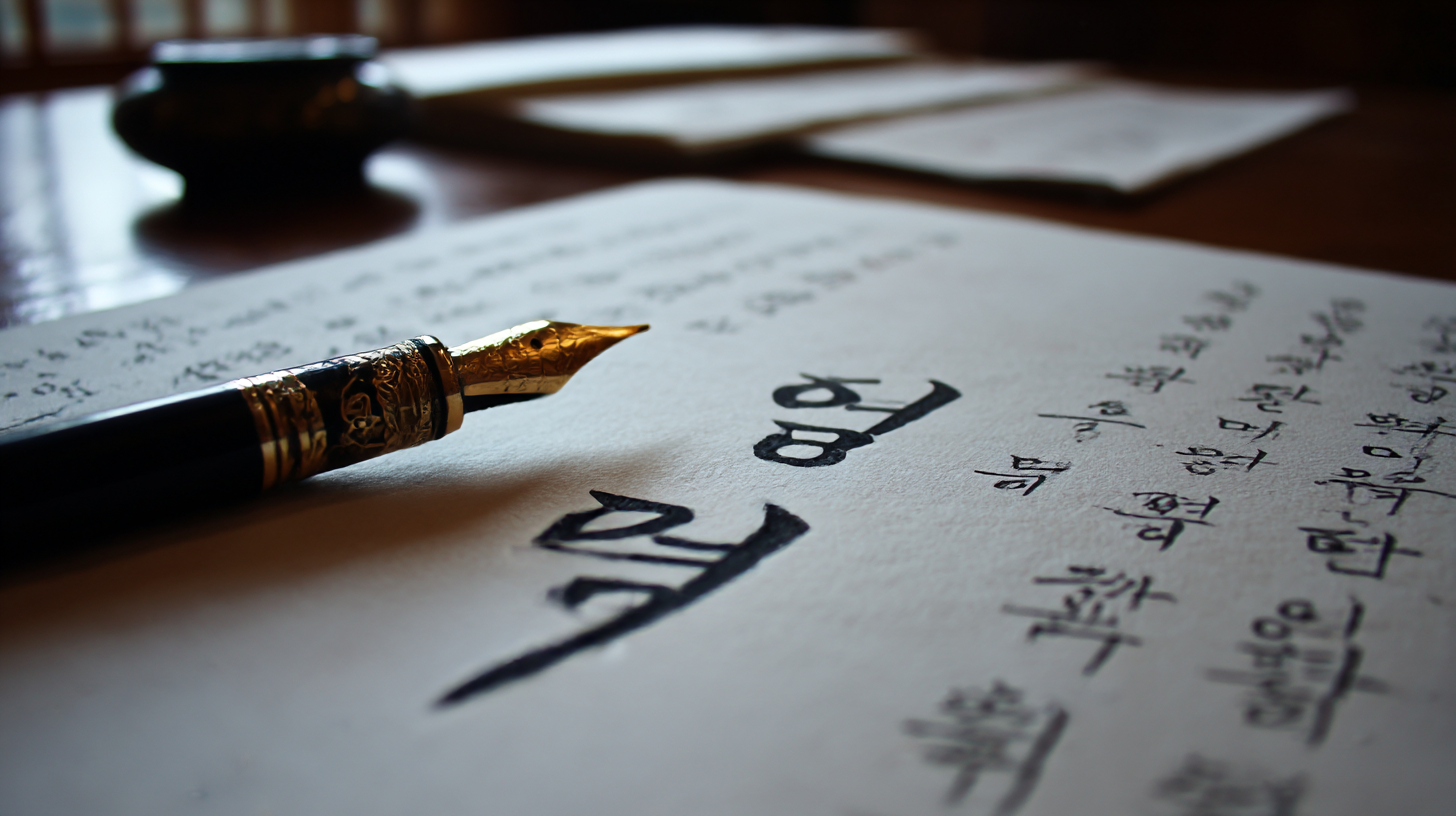
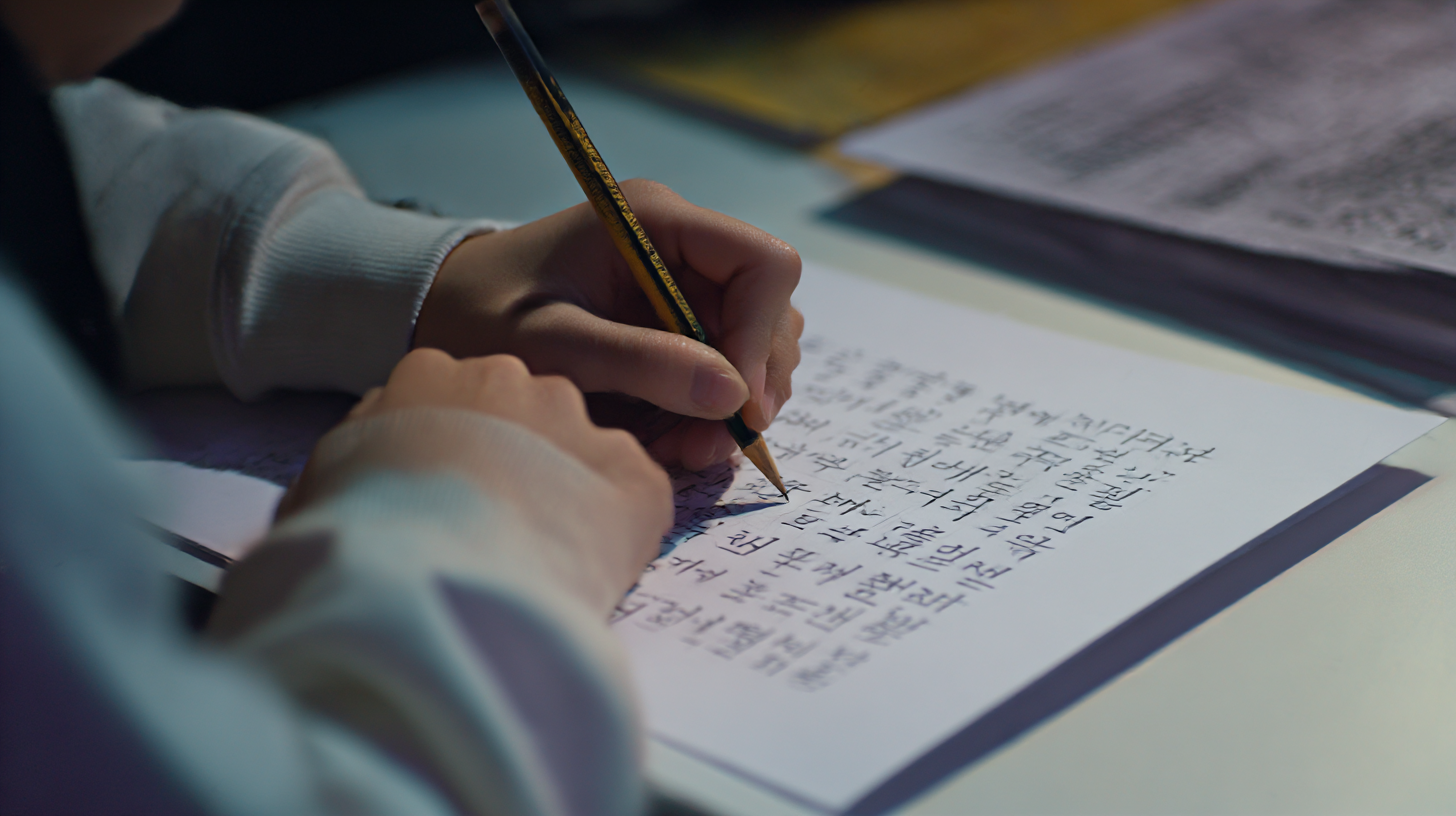
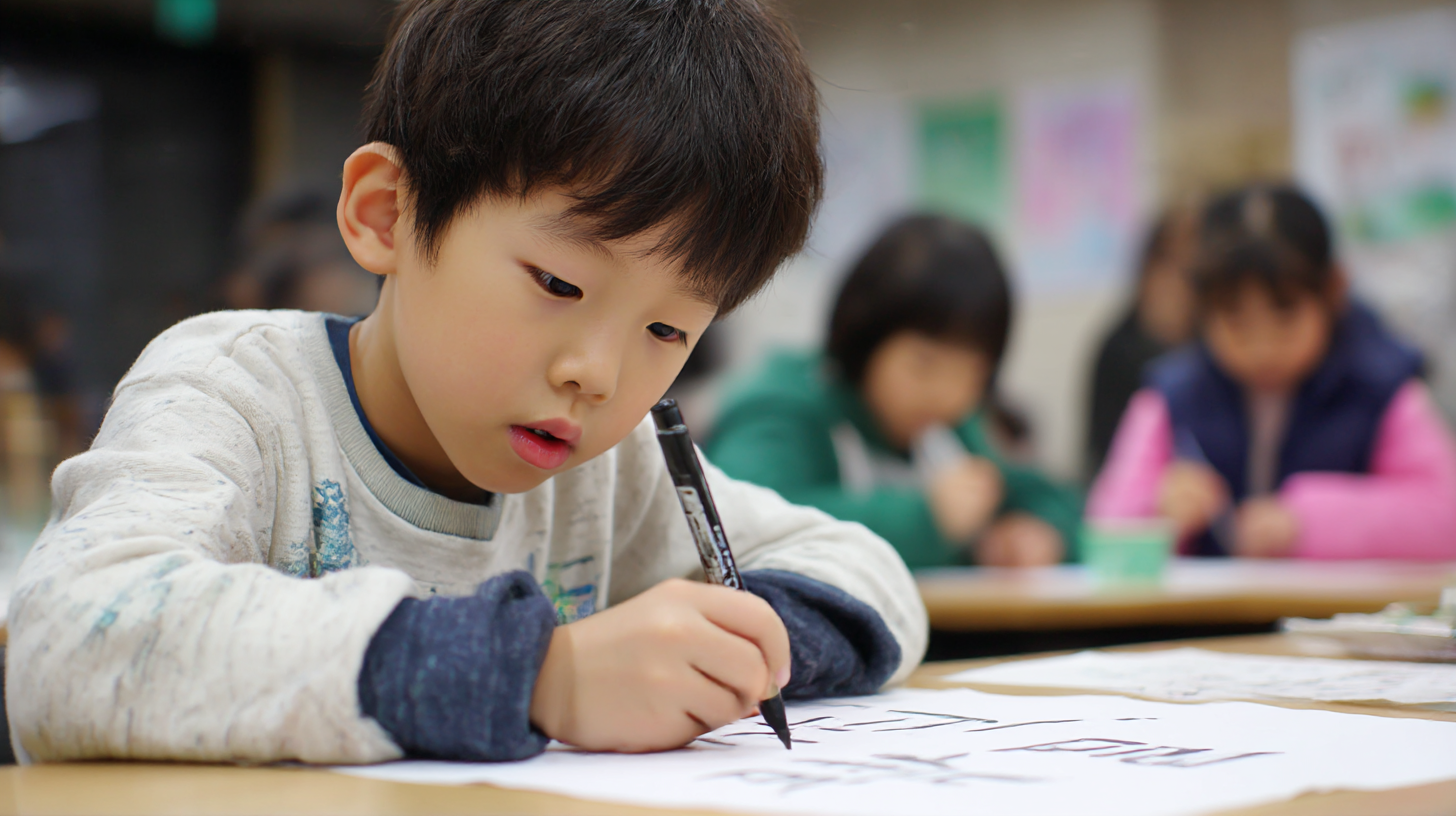
바른글씨 따라쓰기 효과적인 연습법 글씨는 그 사람의 첫인상을 결정짓는 요소 중 하나예요. 디지털 시대에도 손글씨의 가치는 여전히 유효하죠. 특히 학생이나 직장인들 사이에서는 바른 글씨체를 통해 가독성을 높이고, 집중력까지 향상시키는 효과를 기대할 수 있답니다.
이번 글에서는 따라쓰기 연습을 통해 어떻게 바른글씨를 만들 수 있는지, 실질적으로 도움이 되는 루틴과 도구, 그리고 많은 사람들이 겪는 궁금증까지 하나하나 풀어보려 해요. 직접 경험한 듯한 생생한 꿀팁도 가득 담았으니 끝까지 읽어보세요!
✍ 바른글씨의 중요성
글씨는 단순한 기록 수단이 아니라, 자신의 생각을 시각적으로 표현하는 방식이에요. 사람마다 글씨체가 다르기 때문에, 글씨만 봐도 그 사람의 성격이나 정서를 느낄 수 있어요. 예를 들어, 정갈하고 반듯한 글씨를 보면 그 사람의 성실함이 느껴지고, 흐트러진 글씨에서는 급한 성격이나 산만함이 느껴지기도 하죠.
바른글씨는 첫인상에서 중요한 역할을 해요. 이력서를 쓸 때나 메모를 남길 때, 손으로 쓴 글이 상대방에게 주는 인상은 꽤 크답니다. 글씨가 깔끔하면 내용까지 더 신뢰감 있게 느껴지는 법이죠. 특히 교사, 강사, 디자이너처럼 손글씨를 많이 활용하는 직업군에서는 글씨체가 곧 전문성을 나타내기도 해요.
또한, 바른 글씨를 쓰는 습관은 학습 능력 향상에도 영향을 줘요. 또박또박 정리하며 쓰는 과정에서 내용을 더 깊게 이해하게 되고, 반복적으로 쓰면서 암기력도 자연스럽게 올라가요. 실제로 글씨 교정을 시작한 많은 학생들이 공부에 더 집중하게 됐다고 말하곤 해요.
내가 생각했을 때 글씨는 자기관리의 시작이에요. 바른 글씨를 쓰기 위한 꾸준한 노력은 결국 자신의 삶을 정리하고 다듬는 과정과도 같거든요. 단순히 ‘예쁘게 쓰는 것’이 목적이 아니라, 자신을 표현하고 소통하는 더 나은 방식을 찾는 것이라 할 수 있어요.
바른글씨는 마음가짐까지 달라지게 해요. 글씨를 정갈하게 쓰려고 하면 몸도 자연스레 자세를 고치게 되고, 집중도도 올라가죠. 이런 작은 변화가 일상 전반에 긍정적인 영향을 주게 되니까, 단순히 글씨 연습이라고 가볍게 볼 수는 없답니다.
어릴 때부터 글씨 교정을 시작한 사람과 성인이 돼서 시작한 사람 모두에게 효과는 분명해요. 꾸준히만 연습하면 누구나 달라질 수 있는 게 바로 글씨의 매력이에요. 중요한 건 완벽함이 아니라 ‘꾸준함’이죠!
자신의 글씨를 돌아보고 고치고자 하는 마음은 자신을 더 사랑하려는 마음에서 시작돼요. 요즘처럼 빠르게 소비되는 디지털 시대에도 손글씨는 여전히 따뜻함을 전할 수 있는 힘이 있거든요. 메모 한 장, 손편지 하나가 누군가에겐 큰 감동이 되기도 해요.
사실 글씨는 하루아침에 변하지 않아요. 하지만 작은 변화들이 쌓여 어느 순간 ‘예전 글씨와는 완전히 달라졌네!’라는 말을 듣게 될 거예요. 그러니 지금부터라도 가볍게 펜을 들어보는 건 어떨까요? 😊
🖋 글씨체 비교표
글씨체 종류 특징 추천 상황 궁서체 고전적이고 단정함 공문서, 자필 이력서 바탕체 가독성 우수 학습용 필기, 보고서 흘림체 감성적이고 자유로움 손편지, 일기 인쇄체 깔끔하고 정돈됨 노트정리, 플래너 글씨체는 목적에 따라 다양하게 활용돼요. 상황에 맞는 글씨체를 골라 연습하면 훨씬 재미있고 효율적인 학습이 가능하답니다! ✨
🧠 글씨 교정의 효과
바른글씨 연습이 단지 ‘예쁜 글씨를 쓰는 것’에 그치지 않는다는 사실, 알고 있었나요? 꾸준히 따라 쓰다 보면 그 안에서 생각 정리 능력과 집중력이 자연스럽게 자라난답니다. 한 글자씩 정성스럽게 적는 과정이 곧 마음을 다스리는 과정이 되기도 해요.
글씨를 또박또박 쓰기 위해서는 먼저 생각을 정리해야 하죠. 문장을 천천히 써 내려가다 보면 문맥 흐름도 이해하기 쉬워지고, 자연스럽게 글쓰기 실력도 올라가요. 글씨 연습은 언어 감각과 사고력을 동시에 키워주는 최고의 습관 중 하나예요.
아이들의 경우, 글씨체가 바르게 자리 잡으면 학교생활 전반에도 좋은 영향을 준다고 해요. 교과서를 따라 쓰거나 노트를 정리할 때 능률이 오르고, 정돈된 학습 태도를 갖게 돼요. 성인의 경우에도 업무 정리나 플래너 작성, 회의 메모 등에서 능률이 향상되는 효과가 있어요.
정서적 안정에도 도움이 된다는 점이 매력적이에요. 글씨를 쓰는 행위 자체가 명상처럼 차분하게 마음을 가라앉히는 효과가 있거든요. 특히 불안하거나 스트레스를 받을 때 한 글자씩 따라 쓰는 습관은 감정을 정리하는 데 많은 도움이 된답니다.
글씨 교정은 눈에 띄는 외적 변화 외에도 내면적인 만족감을 주기도 해요. 바뀐 글씨체를 보고 스스로 뿌듯함을 느끼는 순간, ‘해냈다!’는 성취감이 생기죠. 이런 긍정적인 감정은 더 나아가 다른 습관 형성에도 좋은 영향을 주게 돼요.
글씨 교정을 시작한 후, 나의 할 일 리스트가 더 깔끔하게 정리되고, 하루의 계획이 명확해졌다는 이야기를 주변에서도 자주 듣게 돼요. 손글씨 연습은 ‘느림의 미학’을 실천하는 하나의 좋은 방법이라고 생각해요. 바쁜 일상 속에서 천천히 나를 돌아볼 수 있는 시간이죠.
글씨를 바꾸는 건 생각보다 큰 도전이에요. 하지만 이 작은 도전을 통해 일상과 마음이 조금씩 정돈되는 것을 느끼면, 단순한 취미 그 이상이 되어버리죠. 그래서 많은 사람들이 이 과정을 ‘마음 치유의 시간’이라고 부르기도 해요.
연습 전과 후를 비교해보면 그 차이는 확연해요. 처음엔 삐뚤빼뚤했던 글씨가 어느새 반듯하게 자리 잡게 되고, 글을 쓰는 손의 움직임도 안정감을 띠게 되죠. 이런 변화를 직접 체감하는 건 정말 신기하고 뿌듯한 일이에요.
이처럼 글씨 교정은 단지 외적인 변화에 머물지 않아요. 집중력 향상, 감정 조절, 성취감, 자기표현까지 두루 챙길 수 있는 유익한 습관이에요. 이제는 ‘왜 바른글씨가 중요한지’ 이해가 되셨죠? 😄
이제 다음 섹션에서는, 실질적으로 어떤 루틴을 따라 연습해야 바른글씨를 만들 수 있는지 구체적으로 알려드릴게요! ✏
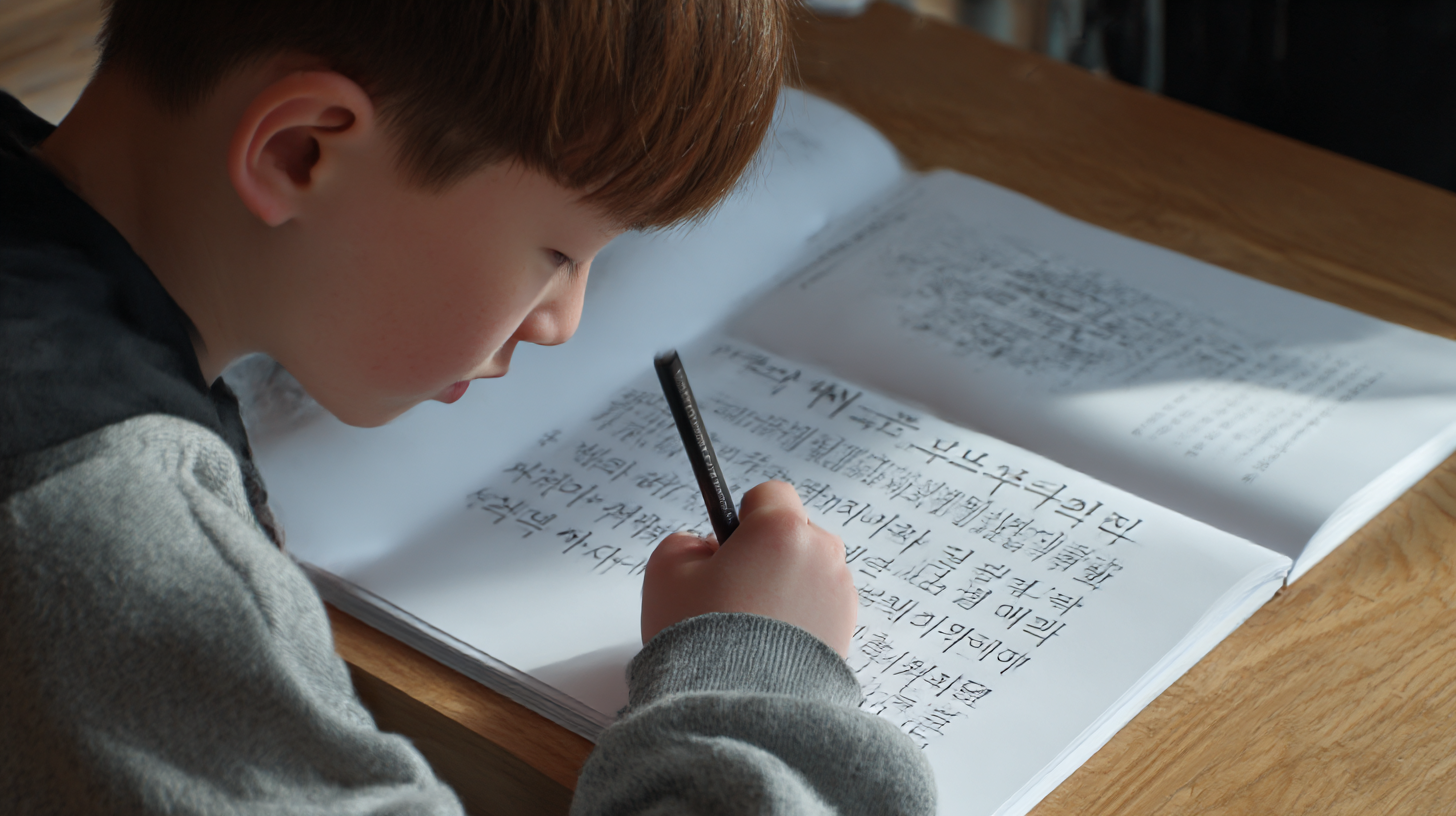
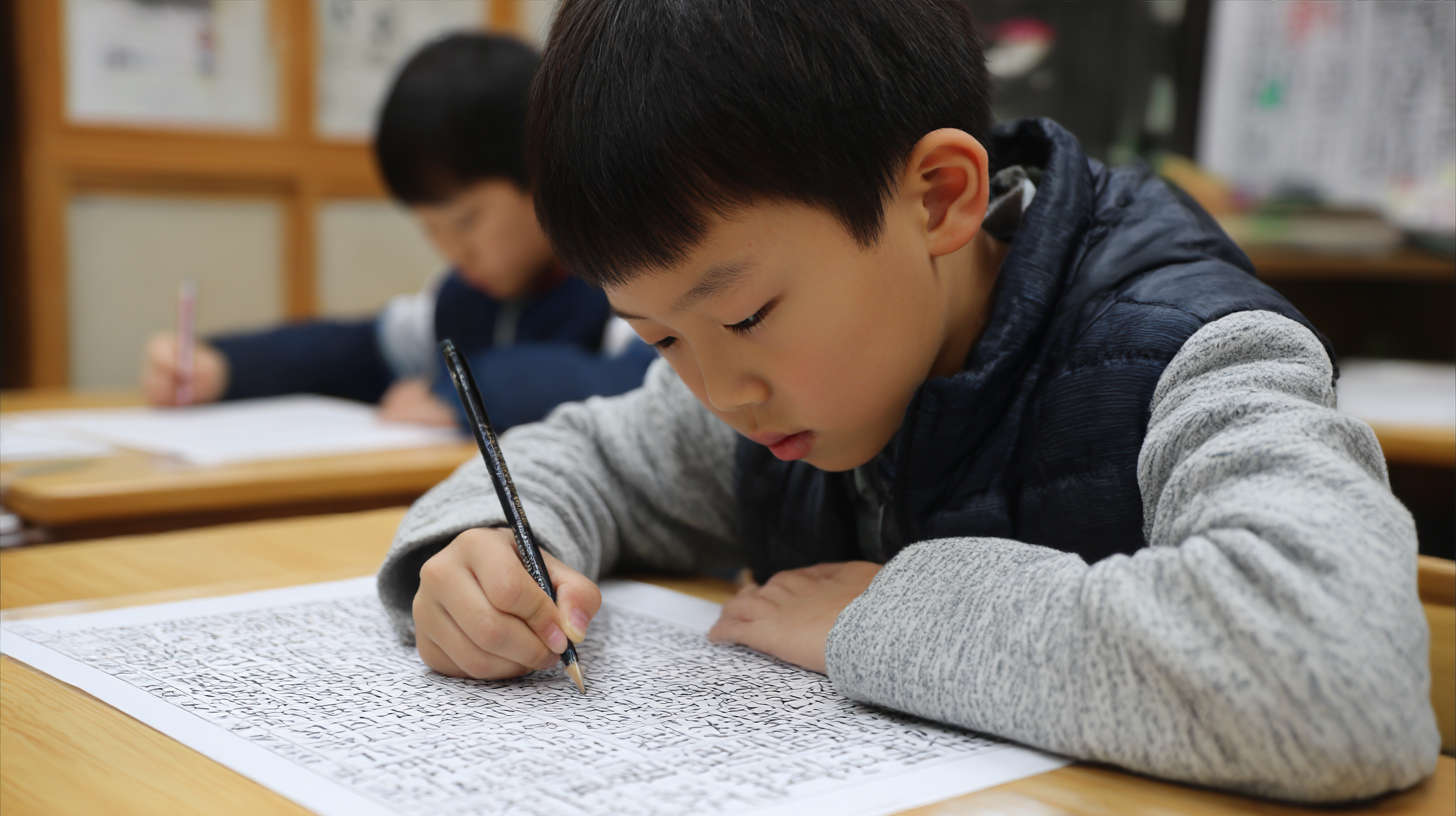
글씨 교정의 효과 📈 글씨 교정 전후 비교표
구분 교정 전 교정 후 가독성 낮음 높음 집중력 흐려짐 향상됨 정서 불안정 안정감 표현력 미흡 풍부 이 표를 참고해서 나의 현재 상태를 진단해보고, 앞으로 어떻게 글씨 연습을 이어나갈지 방향을 잡아보는 것도 좋아요. 다음은 따라쓰기 루틴 소개 들어갑니다! 📘
📘 효과적인 따라쓰기 루틴
바른글씨를 만들기 위한 핵심은 뭐니 뭐니 해도 ‘꾸준한 연습’이에요. 단순히 반복한다고 되는 게 아니라, 체계적인 루틴을 세우고 그에 맞춰 성실하게 따라가는 것이 중요하답니다. 이 섹션에서는 하루 15분으로 시작할 수 있는 실전 루틴을 소개할게요!
첫 단계는 ‘기본 획 연습’이에요. ㅡ, ㅣ, /, ㅁ 같은 직선과 곡선의 형태를 반복적으로 써보는 거죠. 글씨의 뼈대를 단단하게 만들기 위한 가장 기초적인 훈련이에요. 이 과정은 지루해 보일 수 있지만, 글씨 교정의 핵심이라 절대 생략하면 안 돼요.
두 번째 단계는 ‘모음과 자음 단독 연습’이에요. 자음(ㄱ~ㅎ)과 모음(ㅏ~ㅣ)을 또박또박 한 줄씩 적으며 자간과 균형을 잡는 연습을 하는 거예요. 이때부터 글씨가 조금씩 반듯해지는 느낌을 받을 수 있답니다. 연습지에 선을 그어 정렬감을 유지하는 것도 큰 도움이 돼요.
세 번째는 단어 단위로 따라 쓰기예요. 일상에서 자주 쓰는 단어들부터 연습해보세요. ‘감사합니다’, ‘사랑해요’, ‘오늘도 수고했어요’처럼 감정이 담긴 단어를 쓰면 연습이 지루하지 않고, 오히려 힐링처럼 느껴져요. 실생활에서 바로 써먹을 수 있는 표현들이라 실용성도 좋아요.
네 번째는 문장 단위 따라쓰기예요. 명언이나 짧은 시, 좋아하는 노래 가사 등을 골라 하루에 한 문장씩 또박또박 써보는 거예요. 손으로 써 내려가며 문장의 의미도 되새기게 되고, 자연스럽게 글쓰기 감각도 키울 수 있어요.
다섯 번째는 ‘자기 글 쓰기’ 단계예요. 이건 정말 중요한 루틴인데요, 누군가의 글을 따라 쓰는 게 아니라, 내가 느낀 점이나 일기를 짧게라도 직접 쓰는 거예요. 이때부터 글씨에 ‘자신만의 스타일’이 더해지고, 그게 곧 개성 있는 바른글씨가 된답니다!
여섯 번째는 ‘주기적인 피드백’이에요. 일주일 단위로 전후를 비교해보거나, SNS에 올려 다른 사람들과 공유해보는 것도 좋아요. 스스로 개선점을 찾고 인정받는 경험은 동기부여에 큰 도움이 돼요. “생각보다 많이 좋아졌네?”란 말 한마디면 충분히 힘이 되죠!
마지막 단계는 ‘나만의 폰트 만들기’ 도전이에요. 요즘은 손글씨로 폰트를 제작할 수 있는 앱도 많아서, 연습이 어느 정도 궤도에 오른 분들은 나만의 글씨를 디지털로도 남길 수 있답니다. 이건 정말 성취감 폭발이에요! 😍
하루 15분, 일주일 7일만 투자해도 글씨는 놀랍도록 달라질 수 있어요. 중요한 건 ‘매일 조금씩’이라는 꾸준한 자세랍니다. 연습 루틴에 감정을 담는 것도 글씨를 살리는 큰 팁이에요. 😌
다음은 이 연습 루틴을 실행하기 위해 꼭 필요한 도구와 준비물에 대해 알려드릴게요. ✏
🗓 하루 15분 따라쓰기 루틴표
요일 연습 내용 목표 월요일 기본 획 연습 직선/곡선 균형 익히기 화요일 자음/모음 쓰기 자간 정리 수요일 단어 따라쓰기 가독성 개선 목요일 문장 따라쓰기 문장 완성도 향상 금요일 자기 글 작성 표현력 키우기 토요일 피드백 & 복습 개선점 찾기 일요일 폰트 제작 연습 나만의 스타일 정리 지금 이 루틴부터 그대로 시작해보세요! ✍ 평범한 필기에서 감탄 나오는 글씨체로 바뀌는 기적을 느낄 수 있을 거예요.
✏ 필요한 준비물과 도구
바른글씨 따라쓰기 연습을 효과적으로 하려면 준비물도 중요해요. 단순히 연습지만 있다고 되는 게 아니고, 손에 잘 맞는 펜, 눈에 편한 종이, 그리고 동기부여를 줄 수 있는 도구들이 있으면 훨씬 효율적으로 연습할 수 있답니다.
첫 번째 필수 아이템은 ‘중성펜’이에요. 너무 미끄럽지도 않고, 너무 뻑뻑하지도 않은 필감이 연습에는 딱 좋아요. 0.38mm나 0.5mm 정도가 적당하답니다. 특히 제브라 사라사, 모나미 FX153, 제트스트림 같은 제품이 많이 추천돼요.
두 번째는 ‘노트 또는 연습지’인데요, 줄이 있는 노트보다 격자 노트나 점선 노트를 추천해요. 글자의 크기와 간격을 일정하게 맞출 수 있어서 초보자에게 매우 도움이 되거든요. 한 줄 한 줄 정확하게 쓰다 보면 글씨가 훨씬 반듯하게 자리잡아요.
세 번째는 ‘글씨 따라쓰기 교재’예요. 요즘 시중에는 한글 자모 따라쓰기부터 명언 필사까지 다양한 난이도의 교재가 나와 있어요. 무작정 연습하는 것보다, 정돈된 커리큘럼을 따라가는 게 훨씬 효과적이랍니다. 초급용으로는 '손글씨 마스터 노트' 같은 책이 좋아요.
네 번째는 ‘타이머’예요. 단 10~15분만이라도 집중해서 써보세요. 루틴 시간을 정해놓고 타이머로 시간을 체크하면 집중도가 훨씬 높아져요. 뇌도 이 시간을 ‘글씨 연습 시간’으로 인식하면서 몰입도가 올라간답니다.
다섯 번째는 ‘비교용 글씨 샘플’이에요. 처음 시작할 땐 다른 사람의 바른글씨를 보고 따라 쓰는 것이 좋아요. 교재 외에도 인스타그램, 블로그, 유튜브 등에서 다양한 샘플을 구할 수 있어요. ‘이 글씨체를 목표로 해봐야지!’ 하고 설정하면 더 동기부여가 되죠.
여섯 번째는 ‘앱이나 프로그램’이에요. ‘오늘의 손글씨’, ‘바른글씨 연습장’ 앱을 이용하면 하루 단위로 연습할 문장이나 글귀를 추천받을 수 있어요. 디지털 연습도 병행하면 장소에 구애받지 않고 꾸준히 할 수 있어요.
일곱 번째는 ‘글씨 연습 전용 클립보드’예요. 이게 별거 아닌 것 같아도, 종이를 고정해서 흔들리지 않게 쓰면 글씨가 훨씬 안정적으로 나와요. 특히 테이블이 울퉁불퉁하거나 각도가 불편한 장소에서 쓸 땐 아주 유용하답니다.
마지막은 ‘내 글씨를 기록할 앨범 혹은 파일’이에요. 내가 하루하루 써온 글씨들을 모아서 보관하면, 나중에 비교할 때 진짜 감동이에요. 눈에 보이는 발전이야말로 가장 큰 동기부여가 되니까요! ✨
이런 도구들을 활용해서 나만의 ‘글씨 연습 환경’을 만들어보세요. 도구가 좋아야 결과도 잘 나오는 법이니까요! 😄
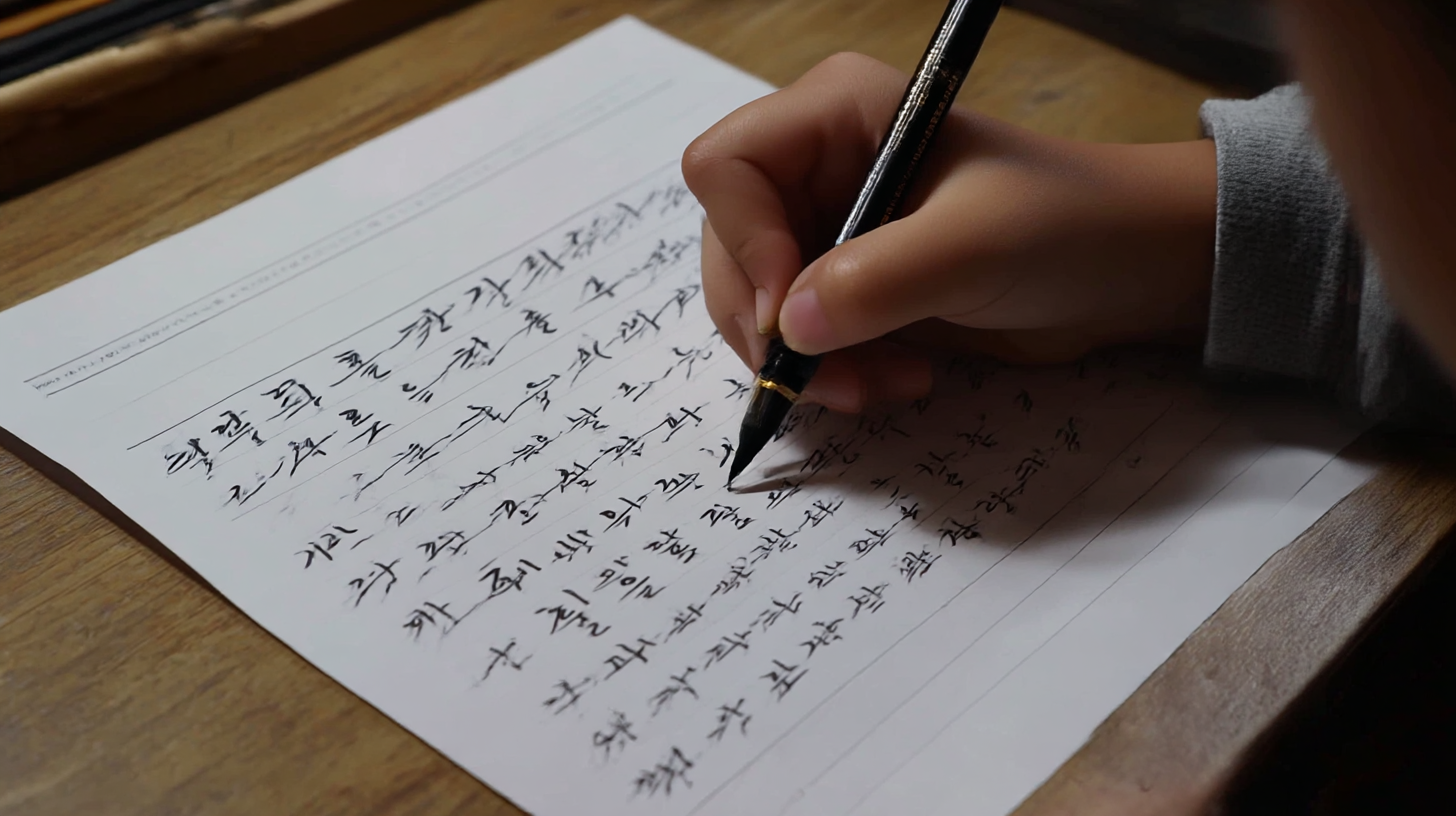
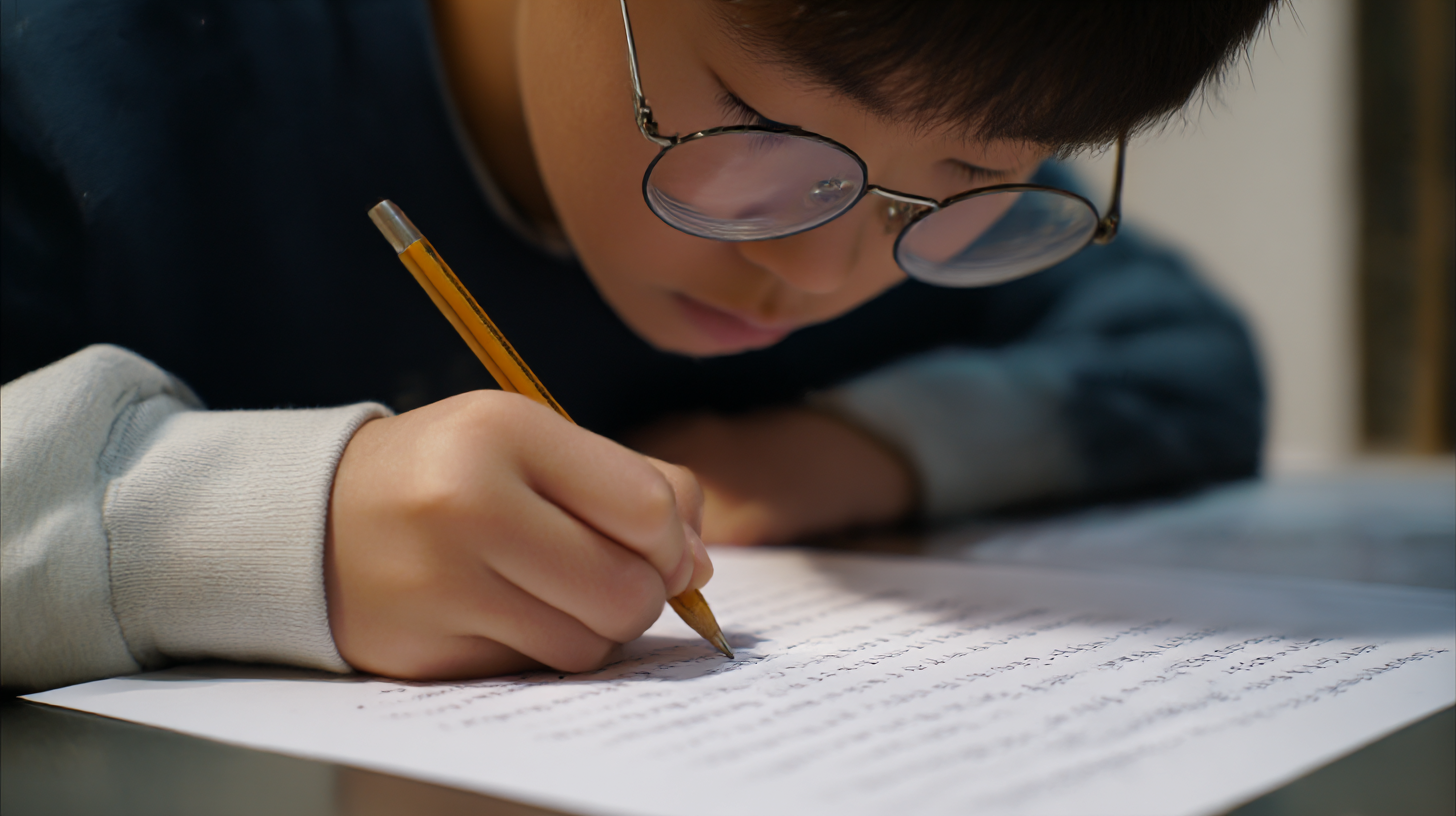
필요한 준비물과 도구 🧰 따라쓰기 추천 도구표
도구 추천 제품 특징 펜 제브라 사라사 필기감 부드럽고 번짐 적음 노트 모눈 노트 자간 맞추기 용이 교재 손글씨 마스터 노트 초보자용 기초 필사 앱 오늘의 손글씨 매일 문장 추천 기능 다음 섹션에서는 글씨 연습으로 실제로 변화된 사람들의 생생한 이야기, 성공 사례들을 소개할게요! 📚
📚 실제 성공 사례 소개
많은 사람들이 글씨 연습을 통해 놀라운 변화를 경험했어요. 단순히 필기체가 예뻐진 걸 넘어서, 자신감이 올라가고 일상까지 더 정돈되었다는 후기가 많답니다. 이번에는 실제 사례를 통해 바른글씨 따라쓰기의 효과를 생생하게 전달해볼게요!
💬 “3개월 연습했더니, 사람들 반응이 달라졌어요!”
직장인 박수진 님(33세)은 글씨체에 대해 콤플렉스가 있었대요. 회의 중 필기를 공유할 때마다 부끄러웠지만, 15분 따라쓰기 루틴을 시작한 후 3개월 만에 깔끔한 인쇄체 느낌으로 바뀌었어요. 이제는 회의록을 맡아달라는 요청까지 자주 받을 정도로 신뢰도 상승!💬 “딸과 함께 시작했어요. 글씨도, 관계도 예뻐졌어요.”
40대 주부 김현정 님은 초등학생 딸과 함께 따라쓰기 책을 구매해 매일 10분씩 연습했어요. 처음에는 딸의 공부 습관을 잡기 위해 시작했지만, 어느새 두 사람 모두 글씨가 예뻐지고, 하루 10분이 소중한 모녀의 시간이 됐대요. “글씨는 덤이고, 마음이 가까워졌어요.”라는 말이 인상 깊었어요.💬 “수험생 시절, 글씨체 바꾸고 점수가 올랐어요.”
대학생 김도윤 님은 수험생 시절 글씨가 엉망이라 시험 중 시간도 오래 걸리고, 채점자도 가독성이 떨어질까 봐 고민이었어요. 그래서 수능 1년 전부터 필기체 개선을 시작했죠. 그 결과, 정리된 노트와 깔끔한 답안이 가산점처럼 작용했고, 결국 원하는 대학에 합격!💬 “손글씨를 상품으로 만들었어요!”
프리랜서 캘리그래퍼 이정민 님은 취미로 시작했던 손글씨 연습이 본업이 되었어요. 인스타그램에 하루 한 문장 글씨체를 올리면서 팔로워가 늘었고, 현재는 기업 브랜딩 작업과 개인 주문 캘리 작업까지 하고 있대요. 글씨 하나로 커리어를 확장한 멋진 사례죠!💬 “학생부에 손편지 썼는데 칭찬받았어요.”
고등학생 유아름 님은 바른글씨 연습을 통해 손글씨가 예뻐졌고, 담임 선생님께 감사의 마음을 손편지로 전달했대요. 그 편지가 학급 게시판에 붙으면서, 친구들에게도 긍정적인 자극이 되었다고 해요. 글씨는 단지 ‘쓰기’ 그 이상이라는 걸 보여준 사례예요.💬 “입사 자기소개서에 손글씨를 활용했어요.”
취준생이던 정유진 님은 자소서 마지막 페이지에 직접 쓴 감사 인사를 손글씨로 작성했어요. 면접관이 그 부분을 인상 깊게 봤다고 하며, 결과적으로 합격 소식을 들었대요. 진심을 전하는 가장 감성적인 방법이 손글씨라는 걸 느낄 수 있었던 사례였어요.💬 “나만의 캘린더를 만들었어요.”
디자인을 전공한 박지수 님은 매년 자신만의 손글씨로 1년치 캘린더를 만들어 가족과 지인들에게 선물해요. 올해는 처음으로 100부를 제작해 프리마켓에 내놓았고, 반응이 정말 좋았대요. “글씨가 내 브랜드가 될 수 있구나”를 실감했다고 해요.💬 “글씨가 달라지니, 내 일상이 달라졌어요.”
무계획적이고 정신없던 하루가, 플래너에 글씨를 정리하며 채워졌어요. 작은 문구 하나에도 의미를 담고 집중하면서, 삶이 ‘가시화’되기 시작했죠. 시각적으로 정리된 일상은 생각보다 큰 변화였고, 결국 ‘내 인생이 예뻐진 느낌’이라는 평까지 나오더라고요.이처럼 많은 사람들이 따라쓰기 연습으로 자신만의 라이프 스타일을 바꾸고 있어요. 다음은, 이 좋은 습관을 꾸준히 이어가기 위한 꿀팁들을 소개할게요! 💡
🏆 따라쓰기 성공 포인트 요약표
포인트 효과 하루 10~15분 투자 꾸준한 습관 형성 글씨 샘플 비교 개선 방향 파악 SNS 공유 동기부여 + 피드백 감성 문구 활용 몰입도 향상 여기까지 따라오셨다면, 여러분도 지금 바로 연습을 시작할 수 있을 만큼 준비되셨을 거예요! 다음 섹션에서는 꾸준히 실천할 수 있도록 도와주는 꿀팁들을 알려드릴게요. 😊
💡 꾸준함을 위한 꿀팁
아무리 좋은 루틴과 도구가 있어도, 꾸준히 실천하지 않으면 효과는 반감돼요. 글씨는 하루아침에 변하지 않기 때문에 ‘지치지 않고 꾸준히’가 핵심이랍니다. 이 섹션에서는 실제로 많은 사람들이 활용하고 있는 글씨 연습 유지 비결을 정리해볼게요! 📘
첫 번째 팁은 ‘글씨 연습 시간 정하기’예요. 하루 중 자신이 가장 편안하게 집중할 수 있는 시간을 글씨 연습 전용 시간으로 정해보세요. 예를 들어 아침 9시, 저녁 10시처럼 일정한 시간에 루틴을 반복하면 몸과 뇌가 자동으로 반응하게 돼요.
두 번째는 ‘작은 목표 세우기’예요. 처음부터 한 페이지, 한 권씩 쓰겠다는 거창한 목표는 실패의 지름길이에요. “오늘은 자음 ㄱ~ㅅ까지”, “문장 하나만 써보자”처럼 작고 쉬운 목표로 시작해보세요. 성취감을 자주 느끼는 게 꾸준함의 비결이에요!
세 번째 팁은 ‘시각적 보상’이에요. 예쁜 스티커나 마스킹 테이프로 연습한 페이지를 꾸며보세요. 노력의 흔적이 예쁘게 남아 있으면, 나중에 펼쳐볼 때마다 뿌듯함을 느낄 수 있어요. 좋아하는 문구를 글씨로 써서 벽에 붙여두는 것도 좋은 방법이에요.
네 번째는 ‘SNS 기록’이에요. 인스타그램, 블로그, 카페 등 어디든 좋아요. #바른글씨 #오늘의손글씨 태그를 달고 연습한 내용을 기록하면 같은 관심사를 가진 사람들과 소통할 수 있고, 자연스럽게 동기부여도 생겨요. 댓글 하나에 또 힘이 나기도 하죠!
다섯 번째는 ‘좋아하는 문장 고르기’예요. 글씨 연습이 지루해질 땐, 좋아하는 노래 가사, 드라마 대사, 명언 등을 골라보세요. 감정이 담긴 문장을 쓰면 글씨에 생기가 돌고, 연습 자체가 힐링처럼 느껴진답니다. ❤
여섯 번째는 ‘환경 만들기’예요. 깔끔한 책상, 좋은 조명, 마음에 드는 펜 하나. 이런 환경은 글씨 연습의 집중도를 높여줘요. 카페나 도서관 같은 조용한 공간에서 연습해보는 것도 좋은 방법이랍니다. 분위기가 사람을 움직이거든요!
일곱 번째는 ‘비교 사진 남기기’예요. 연습 첫날과 1주, 2주, 한 달 후를 비교한 사진을 남겨보세요. 발전이 눈에 보일수록 더 하고 싶어져요. 특히 같은 문장을 반복해서 쓰는 방식으로 비교하면 효과가 확실히 보인답니다.
여덟 번째는 ‘함께하는 사람 만들기’예요. 친구나 가족, 동료와 함께 시작하면 재미도 두 배, 지속력도 세 배예요. 서로 피드백을 주고받거나 작은 미션을 만들어 실천해보는 것도 좋아요. 함께할 때 더 멀리 간다는 말, 여기서도 통하죠! 😊
마지막 팁은 ‘나를 칭찬하기’예요. 매일 쓰고 있다는 것만으로도 대단한 일이에요. “나는 오늘도 나를 위해 한 걸음 나아갔다”는 마음으로, 매 연습 후 스스로에게 칭찬 한마디를 해주세요. 꾸준함은 결국 나를 믿는 마음에서 출발하니까요. ✨
📝 꾸준함을 위한 실천 체크표
실천 항목 추천 빈도 유지 팁 글씨 연습 시간 고정 매일 15분 타이머 활용 SNS 공유 주 2~3회 태그 사용 감성 문장 따라쓰기 주 1회 좋아하는 노래/명언 전후 비교 사진 남기기 2주 단위 같은 문장 반복 이제 진짜 마지막 파트! 사람들이 가장 자주 묻는 궁금증, FAQ에서 실전적인 해답들을 모아봤어요. 😎
❓FAQ
Q1. 글씨 교정 효과는 얼마나 걸리면 보이나요?
A1. 평균적으로 2주~4주 정도 꾸준히 연습하면 눈에 띄는 변화가 나타나요. 하루 15분씩만 투자해도 충분히 효과가 있답니다!
Q2. 나이가 들어도 글씨체를 바꿀 수 있을까요?
A2. 물론이에요! 나이는 전혀 상관없어요. 오히려 성인은 의지와 계획력이 있어서 더 빠르게 변화할 수 있어요.
Q3. 어떤 펜이 글씨 연습에 제일 좋나요?
A3. 중성펜 0.38mm~0.5mm가 가장 적당해요. 제트스트림, 모나미 FX153, 사라사 시리즈가 추천돼요.
Q4. 손이 떨려서 글씨가 흐려지는데 어떻게 해야 하나요?
A4. 펜을 너무 세게 잡지 말고, 종이를 클립보드에 고정해보세요. 천천히 쓰는 연습을 반복하면 떨림이 줄어요.
Q7. 하루에 얼마나 써야 효과가 좋을까요?
A7. 하루 10~15분이면 충분해요. 중요한 건 꾸준함이지 시간의 양이 아니에요!
Q8. 예쁜 글씨체를 따로 배워야 하나요?
A8. 아니에요! 예쁜 글씨체를 흉내 내며 따라쓰는 것만으로도 충분히 교정 효과를 볼 수 있어요. 자신만의 스타일이 자연스럽게 생겨요.